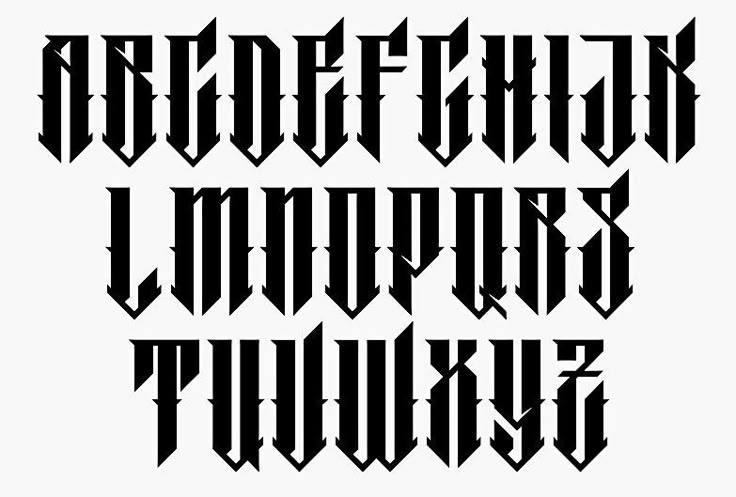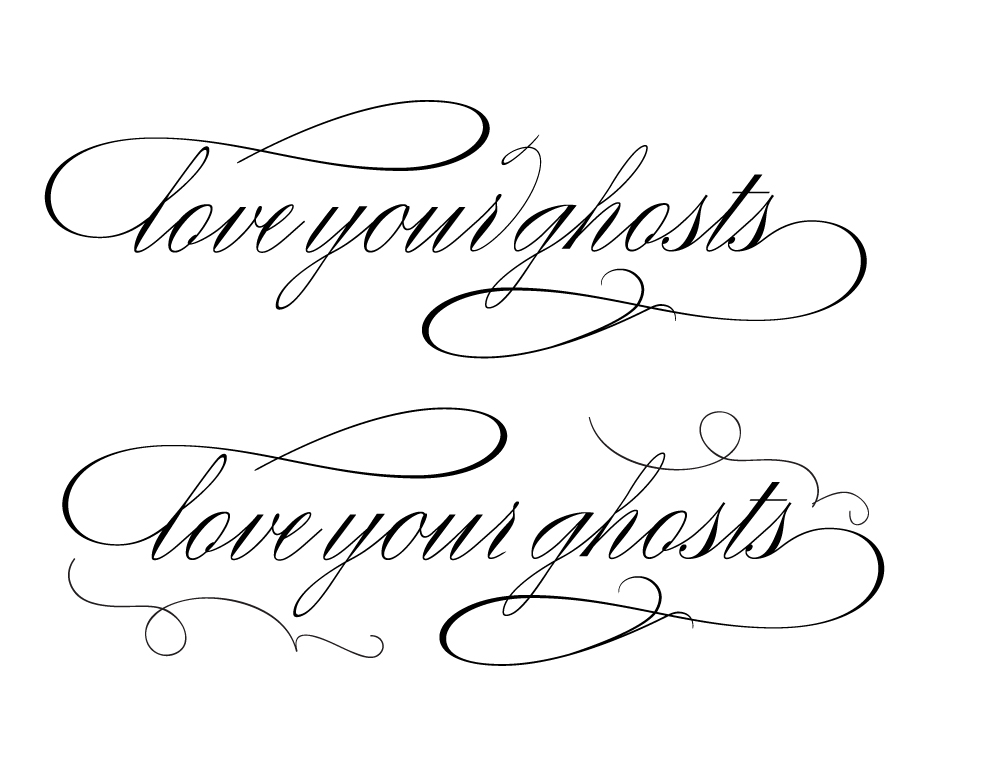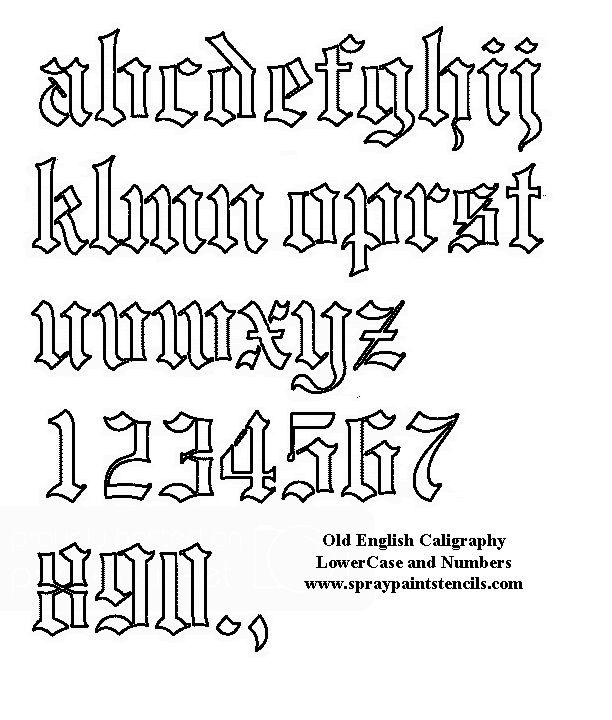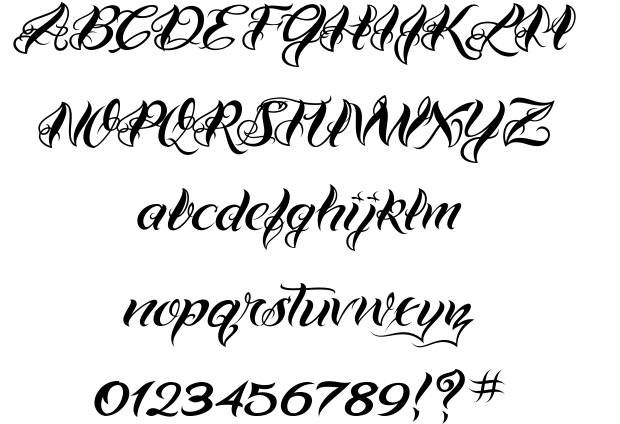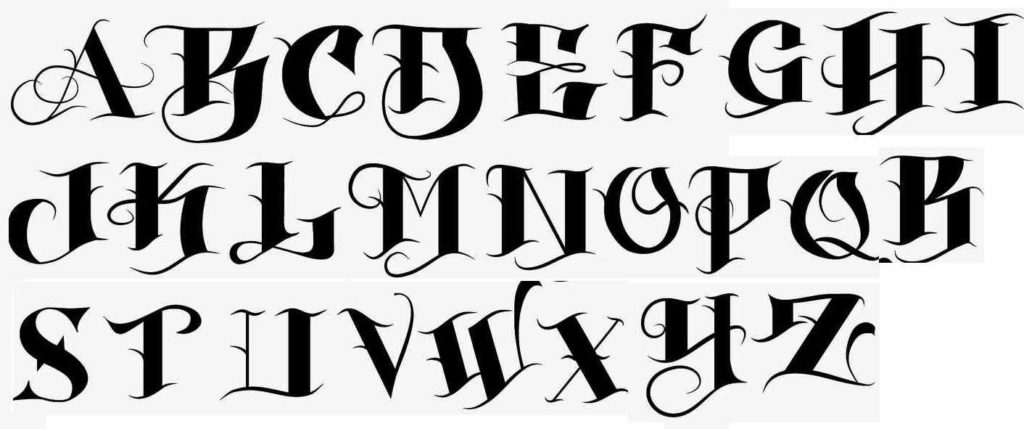
Татуировки в виде надписи – это оригинальный и привлекательный вариант, пользующийся спросом, как среди парней, так и среди девушек.
Для того чтобы текст был выразительным и красивым, привлекал к себе окружающих необходимо выбрать шрифт, количество которых практически безгранично. Нет никакой разницы, первая татуировка это будет или нет, но для того, чтобы правильно выбрать шрифт необходимо запастись терпением. При этом важно учитывать стиль и размер слов, их месторасположение, цвет, а также наличие наклона.
Шрифты для тату и их особенности
При выборе татуировки многие отдают предпочтение надписям, ведь они выглядят привлекательно и оригинально, могут скрывать за собой особый тайный смысл. Более того, часто бывает так, что тату в виде надписи имеет более глубокое значение, чем какой-нибудь рисунок. Однако для того чтобы татуировка была максимально привлекательной нужно позаботиться о выборе шрифта.
Представительницы прекрасного пола отдают предпочтение шрифтам с глубокими изгибами и тонкими линиями, дополняя текст узорами и прочим декором. Что касается мужчин, то они обращают свое внимание на жирные печатные буквы с заостренными окончаниями.
При этом необходимо понимать, что шрифт не влияет на значение татуировки, а лишь подчеркивает ее красоту и оригинальность владельца наколки.
Красивый шрифт: выбор языка и дизайна первой буквы
Если просмотреть фотографии готовых работ, то несложно заметить, что особое влияние на выбор шрифта оказывает язык, который используется при создании татуировки. Классический вариант, который является мировым – английский язык, при этом отдают предпочтение каллиграфическому шрифту или вензелю.
Прежде, чем набить татуировку на свое тело важно определить количество слов. Если в надписи фигурирует большая заглавная буква, то ей нужно уделить особое внимание. Вместе с мастером можно подобрать дизайн первой буквы, его особенности, а также ее размер. Многие специалисты предлагают выделять заглавную букву дополнительными элементами, орнаментами или же выполнять ее в другом цвете.
Правильно выбранный шрифт для татуировки в виде надписи – это основа для создания яркой, стильной и привлекательной татуировки.
При этом важно, чтобы надпись была читаемой, иначе вкладываемый в нее смысл может оказаться непонятным. Не желательно использовать близко стоящие тонкие линии, а также слишком мелкий шрифт, так как татуировки визуально превратиться в пятно.
Дизайн и выбор языка для татуировки
Английский язык считается мировым, потому для татуировок он является идеальным вариантом и пользуется большим спросом. При выборе татуировки стоит учитывать, будет ли это каллиграфический шрифт, шрифт с вензелями, единое слово или определенная фраза. При нанесении надписи стоит согласовать с мастером дизайн заглавной буквы, ведь не каждая буква может смотреться идеально. Мастер может предложить дополнить вашу надпись определенными элементами либо цветом. Для подбора тату можно воспользоваться услугой интернета либо тату-салона. Чтобы можно было передать другим людям смысл своей надписи, нужно учитывать несколько правил: легкая читаемость и исключение мелкого шрифта. Самое главное не выбирайте тонкие линии, расположенные очень близко друг к другу.